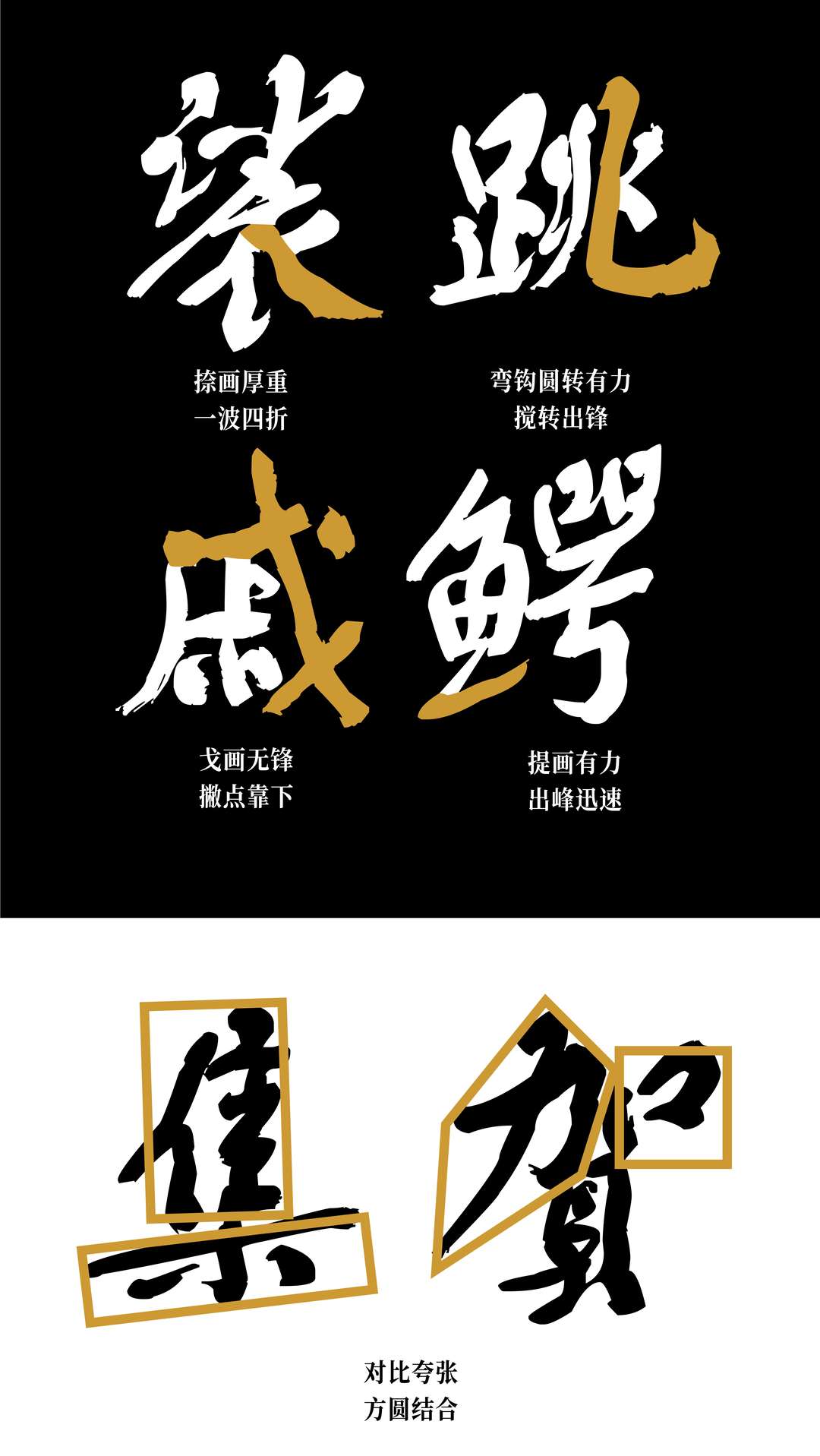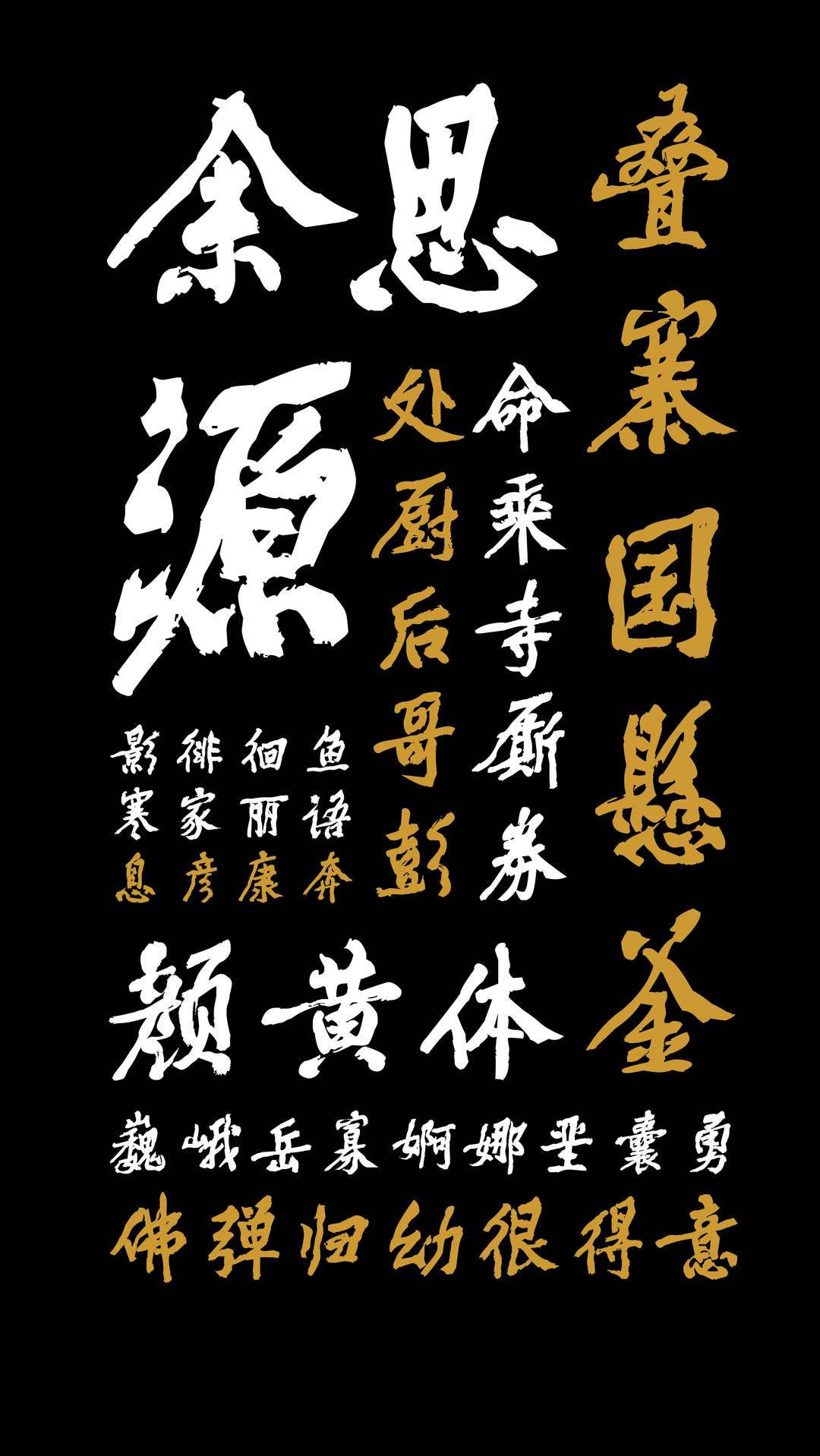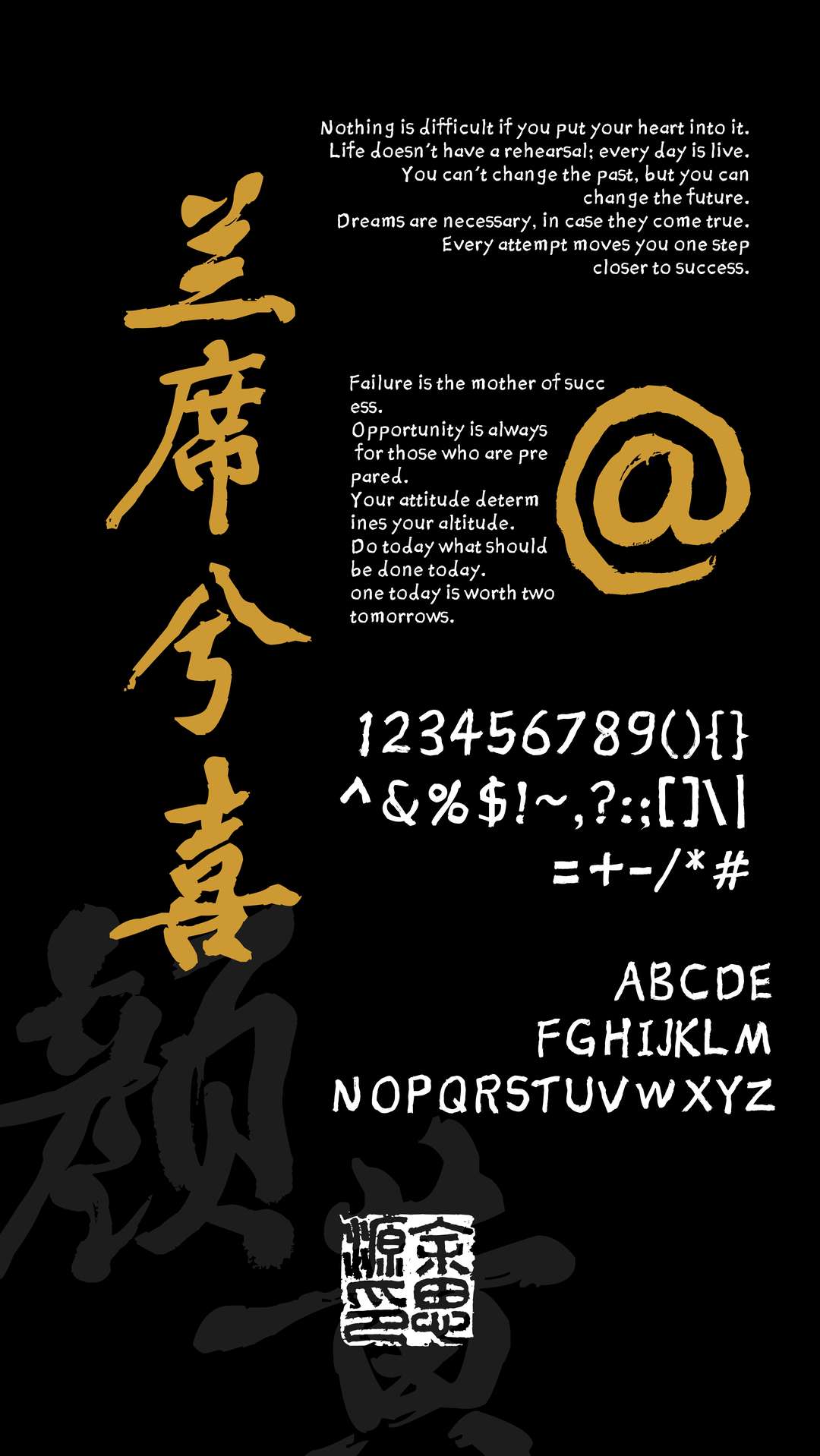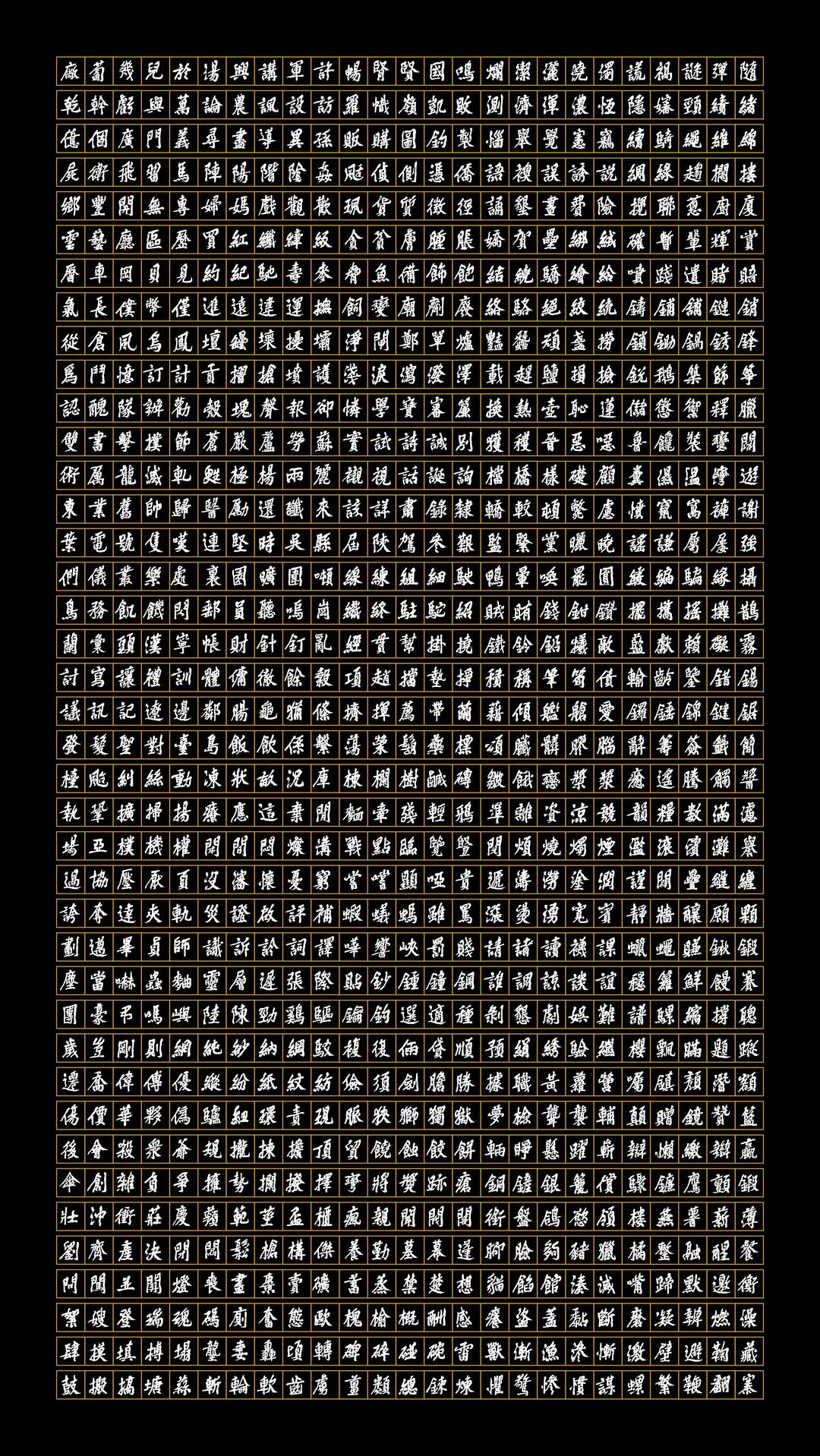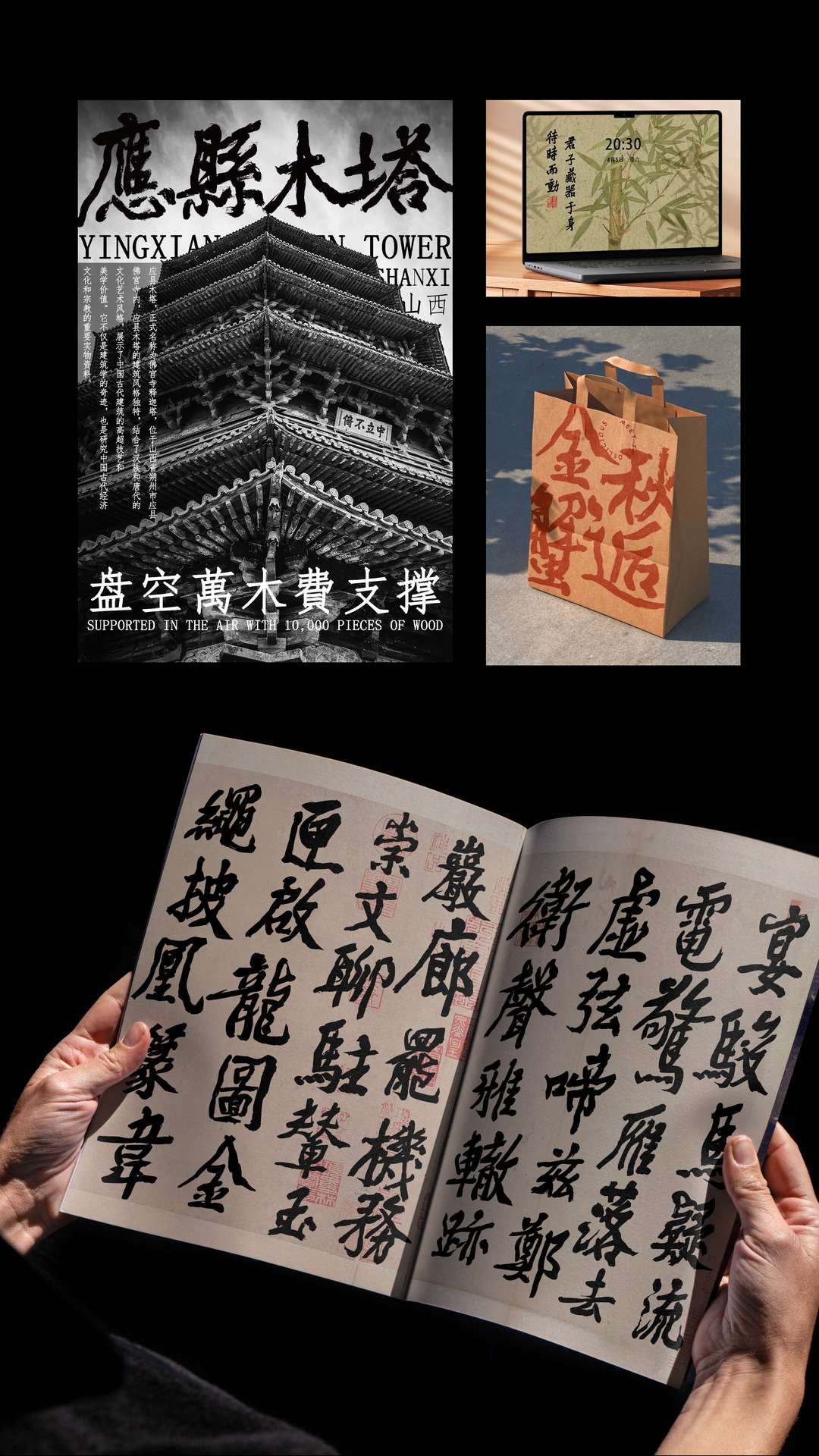
余思源颜黄体
将中唐大书法家颜真卿的书法特点与宋四家之一的黄庭坚的风格结合。颜真卿筋骨的厚重感与黄庭坚的长枪大戟融为一体,实现浑厚酒脱的行楷风格。用笔上保留个人书写习惯的同时表现外拓厚重、撇捺舒展、横画千里阵云等特点,让字体有较强的书法气息又不失设计感。字体强调书法的传承也兼具现代设计的需求。
余思源颜黄体相较于如今市面上的行楷书法字体线条粗细适中,笔法中变化丰富,方圆结合保留了许多字体飞白又不像江湖体般张牙舞爪,辨识度较强,是一款拥有简体中文繁体中文与英文希腊等符号的一款较为完整的行楷书法字体,适用于多类设计场合。
贯通百年书汇聚字体精华
将中唐大书法家颜真卿的书法特点与宋四家之一的黄庭坚的风格结合。颜真卿筋骨的厚重感与黄庭坚的长枪大戟融为一体,实现浑厚洒脱的行楷风格。用笔上保留个人书写习惯的同时表现外拓厚重、撇捺舒展、横画千里阵云等特点,让字体有较强的书法气息又不失设计感。字体强调书法的传承也兼具现代设计的需求。
余思源颜黄体相较于如今市面上的行楷书法字体线条粗细适中,笔法中变化丰富,方圆结合保留了许多字体飞白又不像江湖体般张牙舞爪,辨识度较强,是一款拥有简体中文繁体中文与英文希腊等符号的一款较为完整的行楷书法字体,适用于多类设计场台。